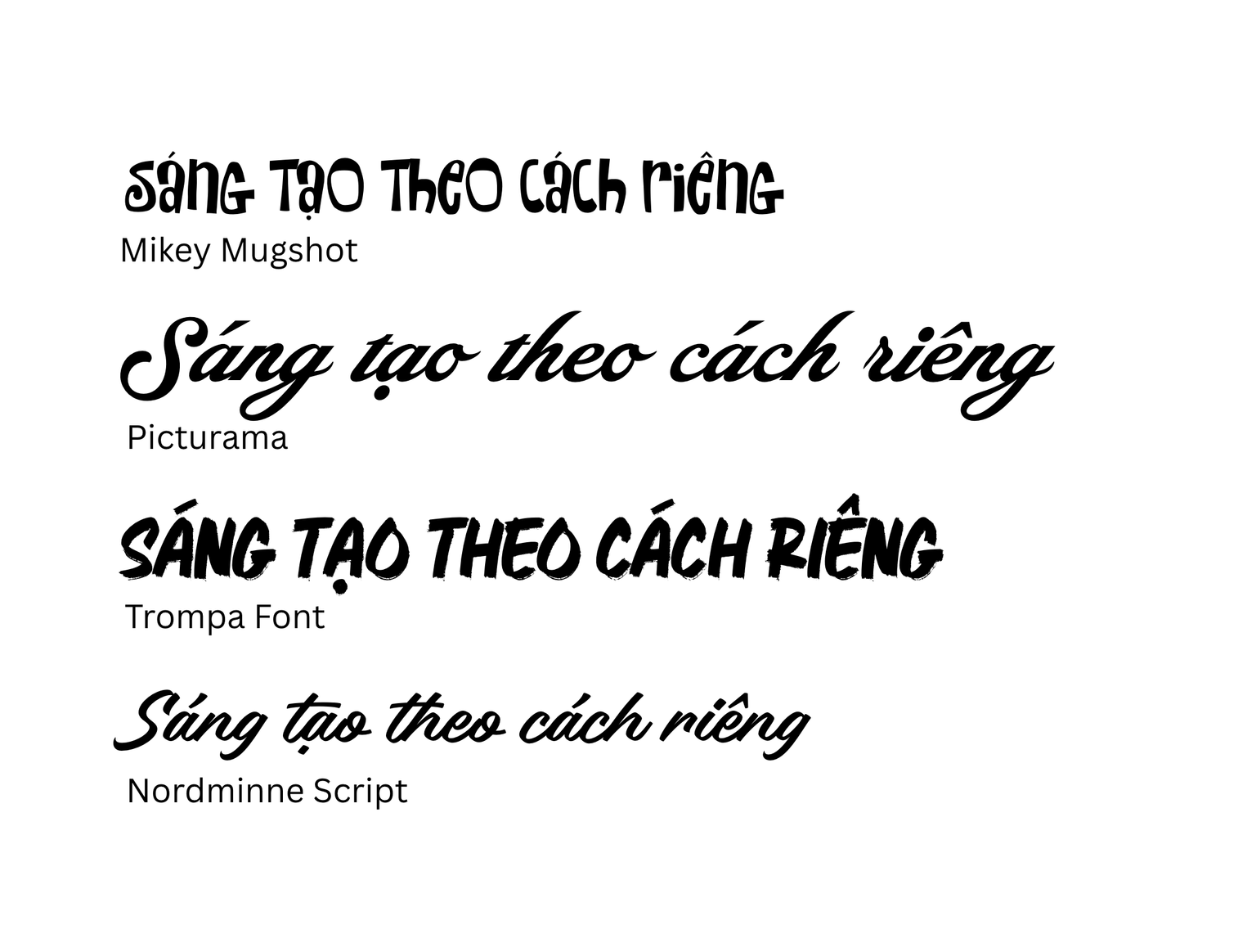
Hơn 100 font tiếng Việt từ Canva Vietnam mang đến nhiều lựa chọn cho những tiêu đề cần cá tính riêng. Mikey Mugshot và Trompa Font tạo cảm giác vui, lạ mắt, còn Better Faster nghiêng về vẻ mạnh mẽ và dứt khoát.
Những thiết kế cần chuyển động có thể tìm thấy nét mực giàu năng lượng ở Tokyo Taiyaki. Picturama, Nordminne Script, Baystar Script và Anaconda Wildstyle lại mở ra các sắc thái mềm mại, phóng khoáng hoặc giàu cảm xúc hơn cho từng câu chữ.
Sự đa dạng này giúp font chữ đẹp tiếng Việt không chỉ là lựa chọn để hiển thị đủ dấu. Kiểu chữ trở thành một phần của thông điệp, góp phần thể hiện tinh thần của poster, bài đăng, thiệp mời hay bài thuyết trình. Khi đặt cùng nội dung và hình ảnh, mỗi font cho thấy cá tính rõ ràng hơn.
Bộ lọc Ngôn ngữ dành cho Tiếng Việt đưa các font liên quan về cùng một danh sách, giúp bạn khám phá nhanh hơn mà không phải mở từng lựa chọn. Bộ sưu tập Phông chữ Tiếng Việt cũng mang đến một điểm bắt đầu tập trung cho nội dung có dấu.
Khả năng hiển thị được đánh giá tốt nhất trong câu chữ thật, từ tiêu đề, tên riêng đến đoạn nội dung dài. Các ký tự như ă, â, ê, ô, ơ và ư giúp bạn nhận ra lựa chọn nào rõ dấu, cân đối và phù hợp với mục đích thiết kế.
Một kiểu chữ phù hợp có thể tiếp tục được phát triển ngay trong trình biên tập Canva. Cỡ chữ, màu sắc, cách căn, khoảng cách và hiệu ứng giúp phần chữ thể hiện đúng vai trò, từ tiêu đề gây chú ý đến nội dung cần đọc nhanh.
Mẫu thiết kế, hình ảnh và thành phần đồ họa cùng nằm trong một không gian sáng tạo, nên mọi thay đổi đều được nhìn thấy trong tổng thể. Bạn dễ cân bằng chữ với hình, tạo thứ bậc rõ ràng và giữ phong cách nhất quán trên từng trang.
Từ một tiêu đề đơn giản, ý tưởng có thể trở thành bài đăng, áp phích, thiệp mời hoặc bài thuyết trình hoàn chỉnh. Khả năng chỉnh trực tiếp trong bố cục thật giúp bạn đưa ra lựa chọn tự tin hơn và sẵn sàng chia sẻ mà không phải chuyển qua công cụ khác.
Canva AI mang đến điểm khởi đầu khi bạn đã có chủ đề nhưng chưa tìm được câu chữ hoặc bố cục phù hợp. Công cụ có thể gợi ý nội dung hay tạo một bản thiết kế ban đầu vẫn chỉnh sửa được, để ý tưởng sớm thành hình.
Từ bản gợi ý, bạn tiếp tục điều chỉnh thông điệp, thay font và lựa chọn phong cách hợp với người xem. Việc kiểm tra dấu tiếng Việt trên chính nội dung được tạo giúp phần chữ vừa đúng ý vừa giữ được độ rõ ràng trong thiết kế.
Kiểu chữ phát huy tốt nhất khi có vai trò rõ ràng trong toàn bộ thiết kế. Font giàu cá tính tạo điểm nhấn cho tiêu đề, trong khi một lựa chọn dễ đọc hơn giúp phần thông tin dài giữ được nhịp và không làm người xem mệt.
Cỡ chữ, độ đậm, khoảng cách và cách căn tạo nên thứ bậc thị giác, dẫn mắt từ thông điệp chính đến các chi tiết bổ sung. Sự cân bằng giữa chữ, hình ảnh và khoảng trống giúp bố cục trông chỉn chu mà vẫn truyền tải nội dung nhanh.